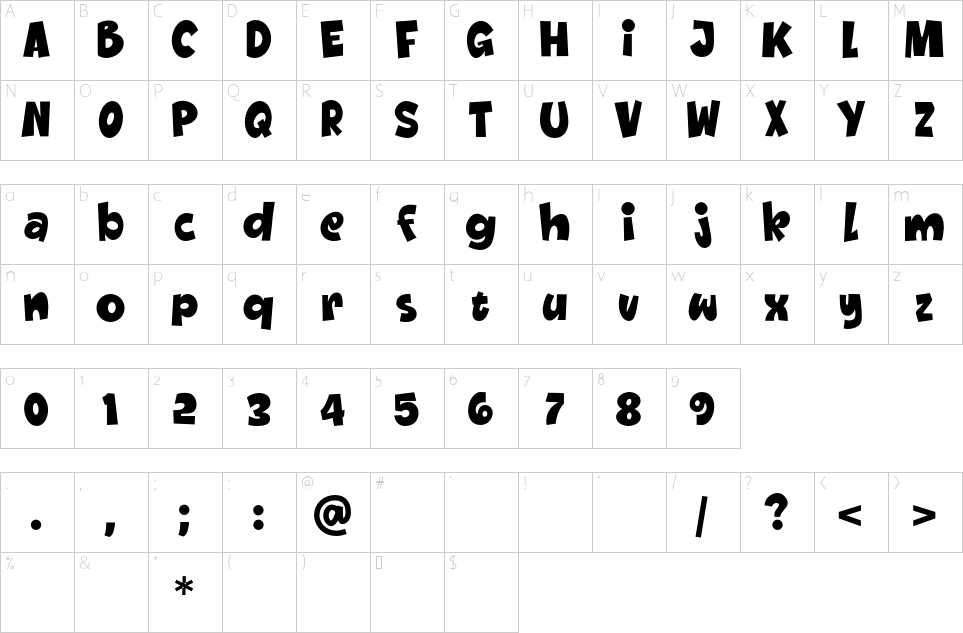
A fonte Monkey Dancing é uma opção gratuita e divertida para quem procura um estilo único e vibrante. Desenvolvida pelo estúdio Afkari Studio, esta fonte é perfeita para dar um toque especial aos seus projetos digitais. Com uma design inspirado na dança de macacos, Monkey Dancing adiciona um brilho inusitado à sua página web, logo, ou qualquer projeto impresso. Se você está procurando por uma fonte que seja tanto utilidade quanto um charme visual, essa pode ser a escolha certa. Com seu download de 474 vezes, é claro que esta font não deixa a desejar. Uma ótima fonte para quem busca algo que seja original e divertido para o trabalho ou a diversão. Descubra Monkey Dancing e veja como ela pode transformar sua experiência em design.